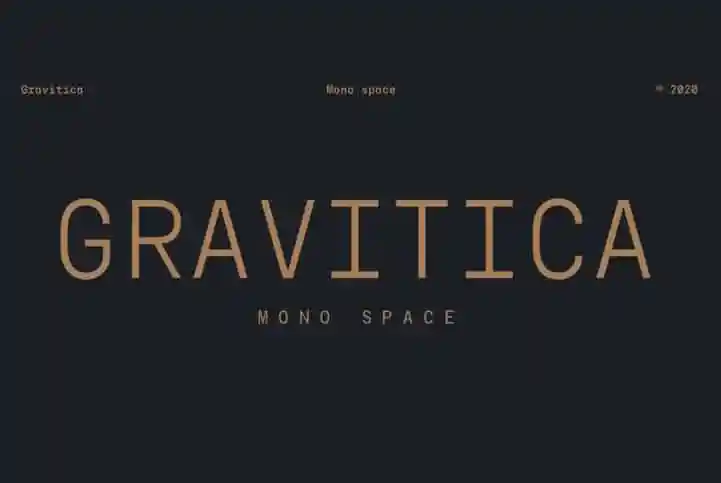
Gravitica Mono Sans Serif Font – Download Grátis
Gravitica Mono Sans Serif é uma fonte sem serif perfeita para dar seu projeto um toque personalizado. Ela foi criada pelo designer Ckhans Fonts e apresenta 18 estilos (6 pesos, 6 itálicos e 6 ícones), cada um com mais de 508 caracteres. Esta font é especialmente adequada para o design gráfico e qualquer uso de exibição. Além disso, a família de fontes inclui suporte linguístico extenso, frações, figuras tabulares, símbolos, ligaduras e muito mais nos pesos da tipografia. É uma ótima opção para quem busca uma fonte sem serif que pode ser usada em diversos ambientes gráficos.